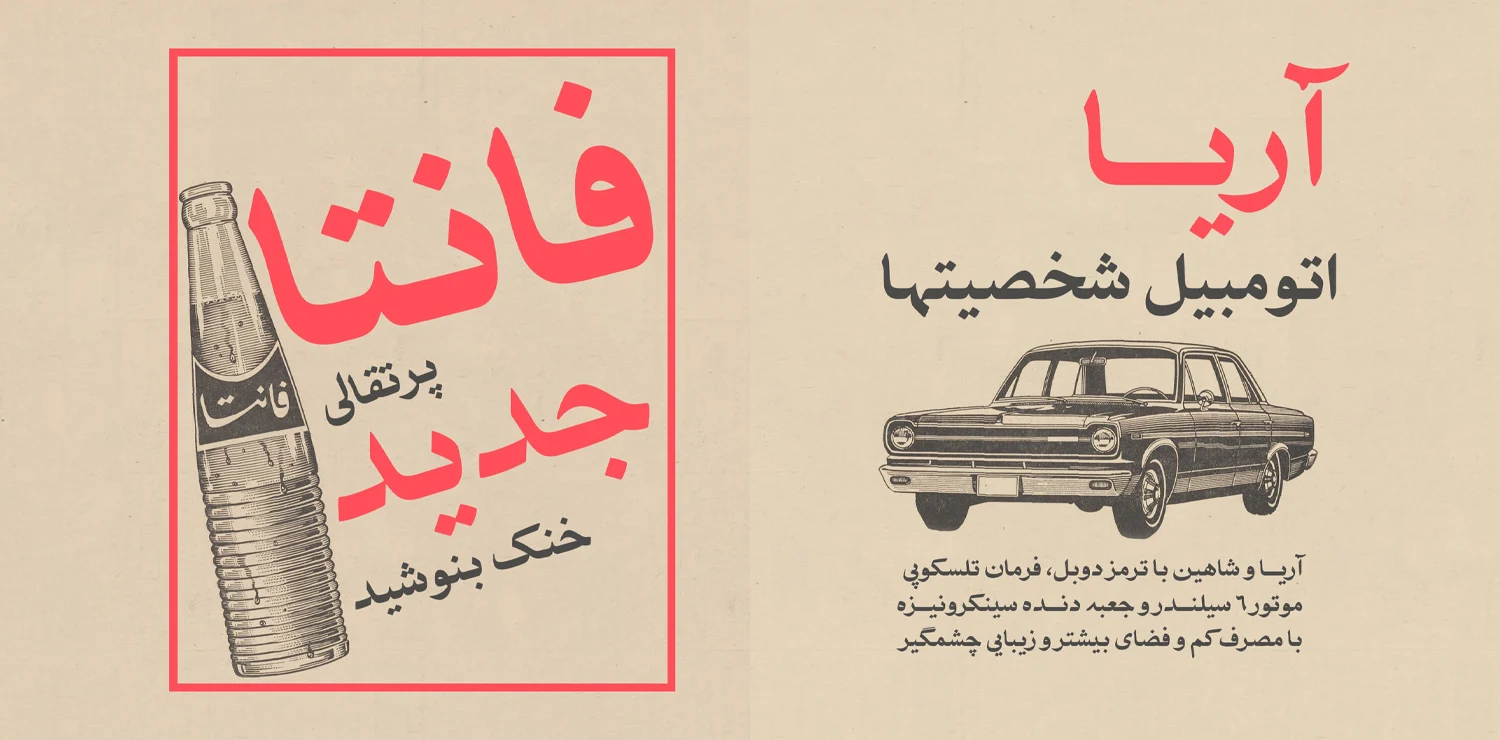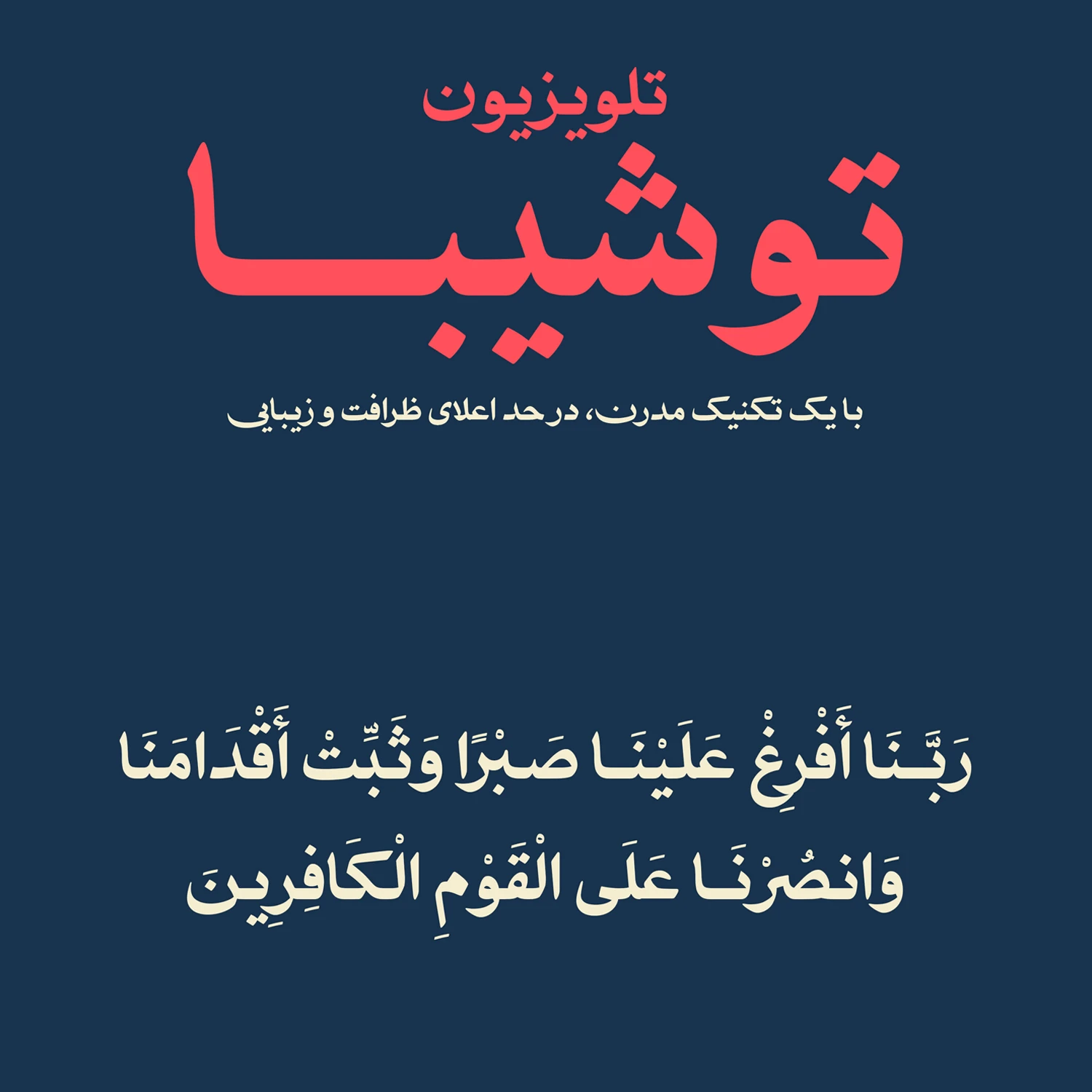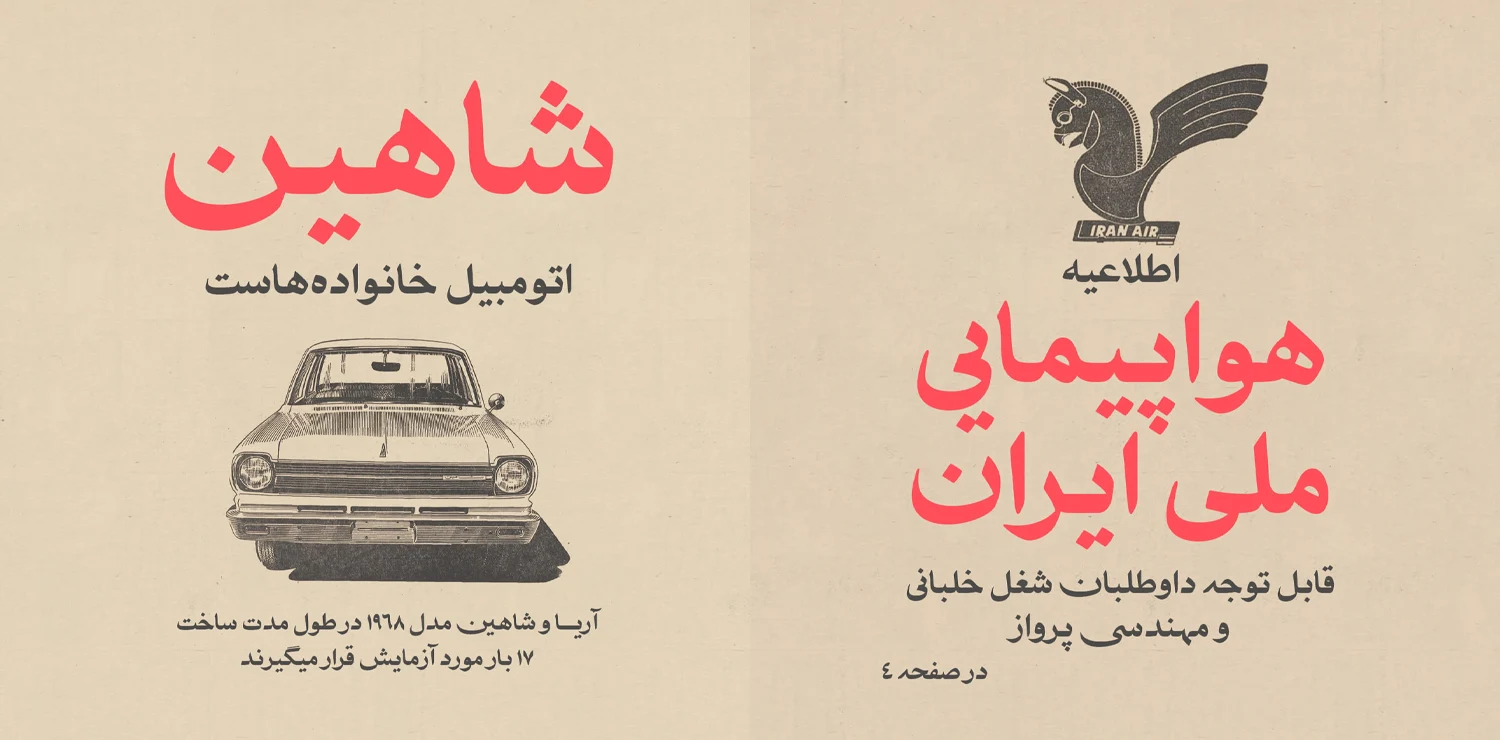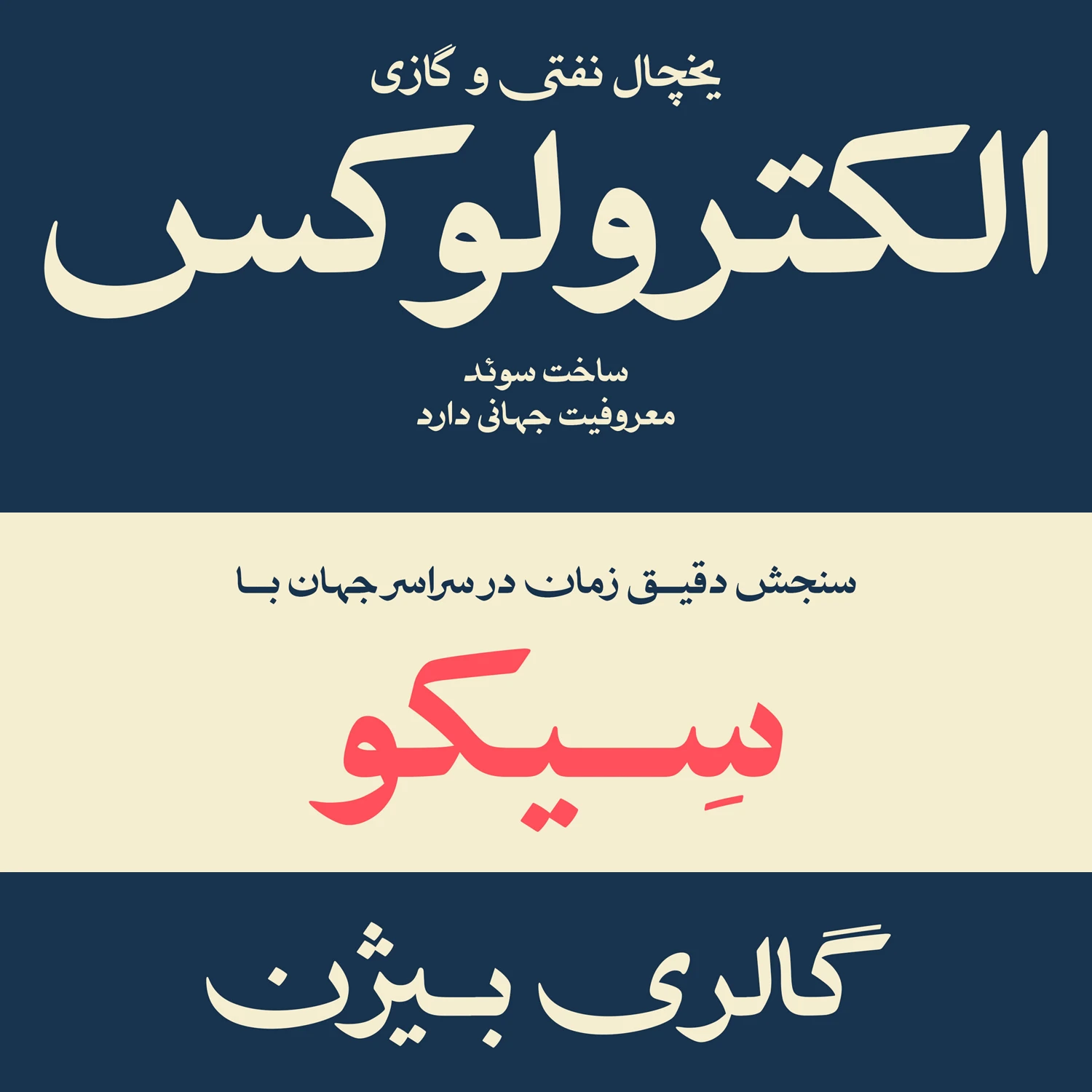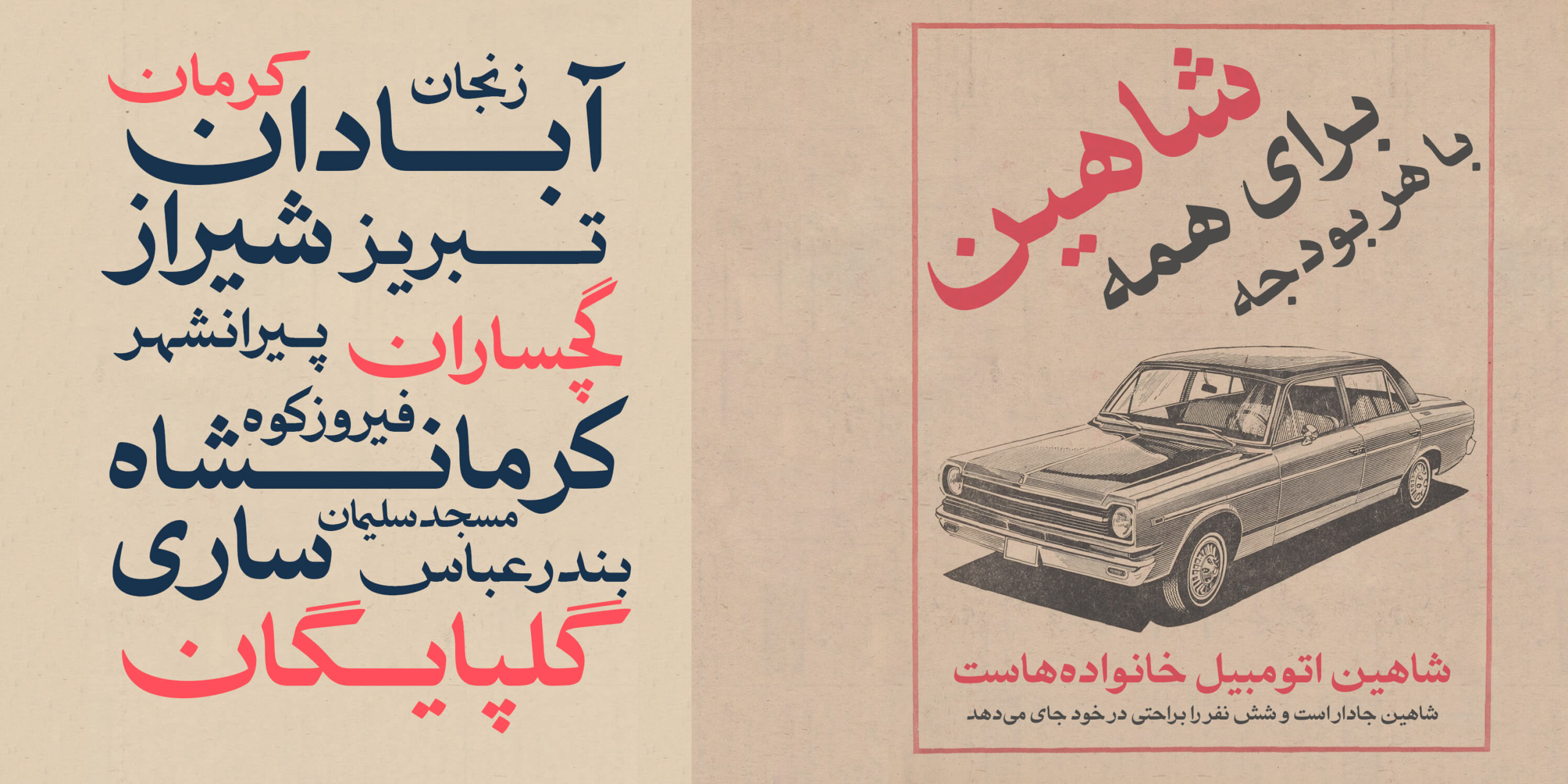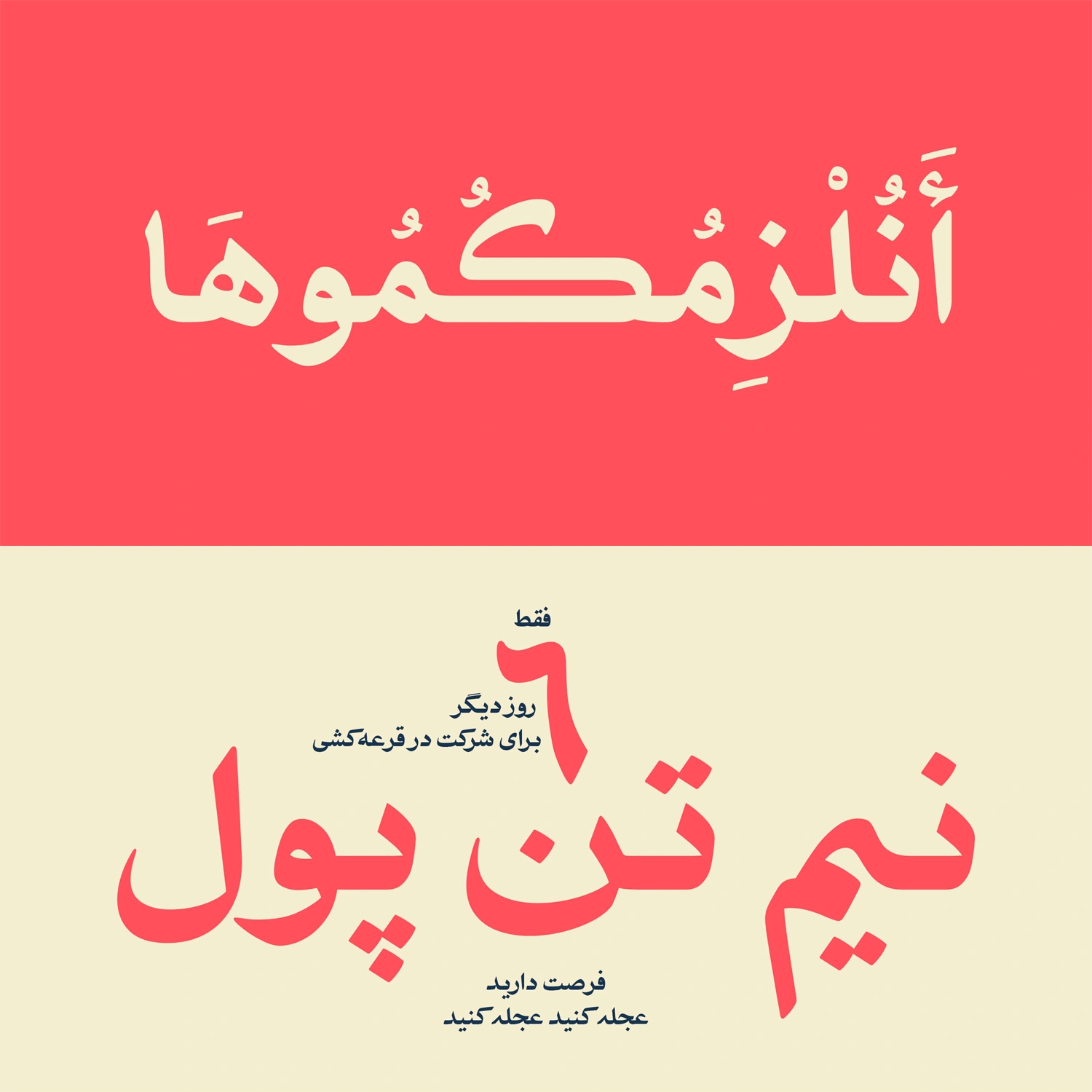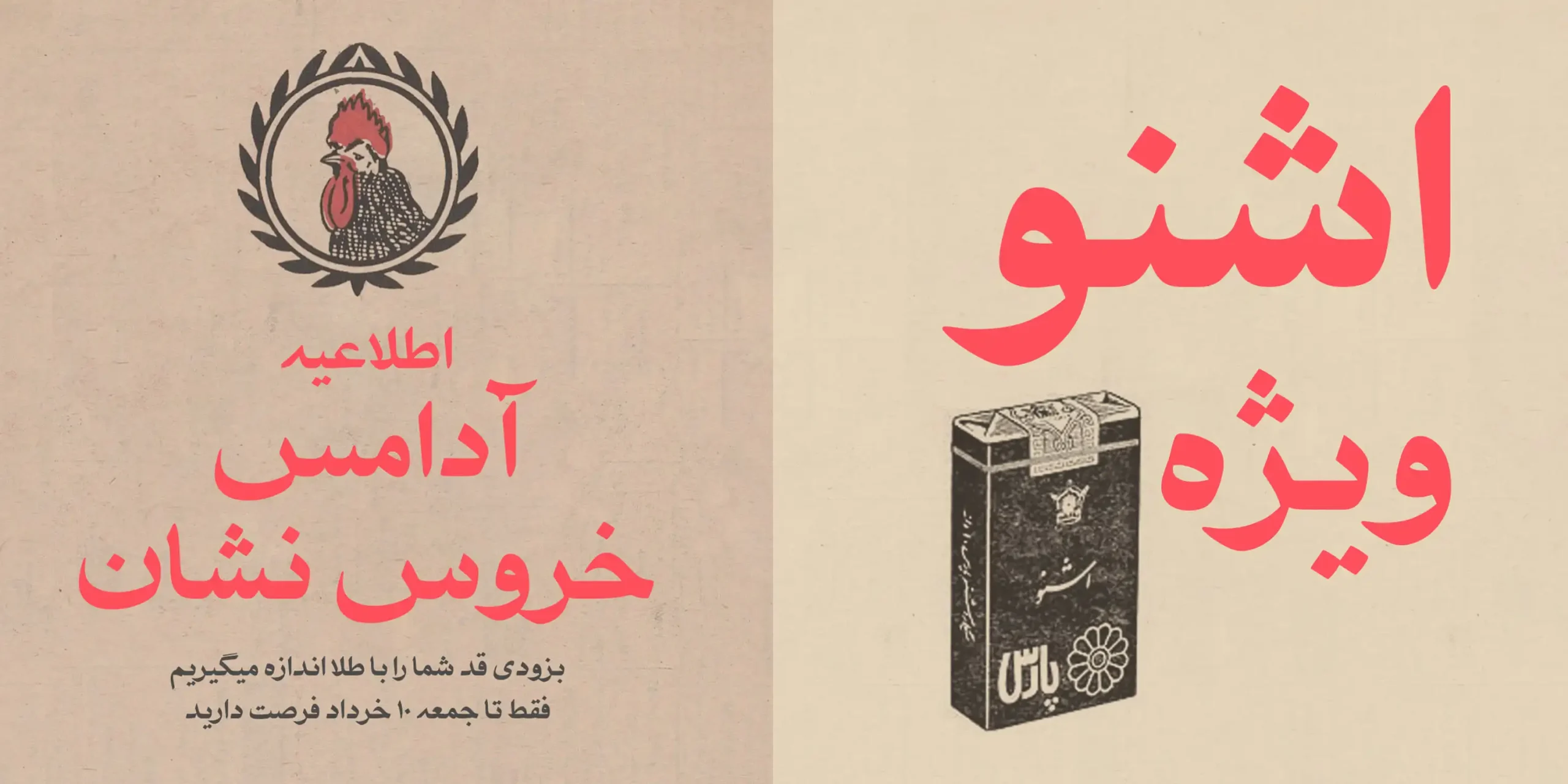
فونت تبلیغ (Tabliq)
| طراح | رضا بهلول |
فونت تبلیغ (به انگلیسی: Tabliq) از سری فونتهای نسخ است که با الهام از تبلیغات روزنامههای قدیمی در دهه ۴۰ و ۵۰ طراحی شده است. این فونت نه تنها نوستالژی را برمیانگیزد، بلکه با فرآیند طراحی دقیق و حرفهای خود، تعادلی هوشمندانه میان ظاهر دستنویس سنتی و استانداردهای تایپوگرافی مدرن برقرار کرده است.
رضا بهلول در طراحی این فونت با اتخاب هوشمندانه اسکلت حروف از نمونههای تاریخی، پالایش مکرر گلیفها و توجه به جزئیاتی چون انحنا، ضخامت، ریتم و خوانایی آن را ایجاد کرده است. نتیجه آن فونتی با بافت نوشتاری یکدست و جذابی است که ساختار فنی و حرفهای خود را بهخوبی نشان میدهد.
فونت تبلیغ برای کاربردهایی که نیاز به حس گرم و خاطرهانگیز مانند تیترهای تبلیغاتی، پوسترها، بستهبندی محصولات با تم وینتیج، پروژههای فرهنگی و هنری، و حتی رابطهای دیجیتال نیازمند حس انسانی هستند، عملکرد خوبی از خود نشان میدهد. این فونت گزینهای ایدهآل برای طراحانی است که میخواهند پیامی صمیمی و واقعی را با ظاهری حرفهای و خوانا منتقل کنند.
این فونت با پشتیبانی کامل از زبان فارسی و عربی، پروژههای تبلیغی و متون کوتاه شما که با هدف تیترنویسی و عناوین منتشر میکنید را با تم دهه ۴۰ و ۵۰ به خوبی نشان خواهد داد. علاوه بر تبلیغات میتوانید برای عنوان مطالب در سایت، تامنیل و پوستر شبکههای اجتماعی و جلد عنوان کتاب و مجله از این قلم استفاده کنید.